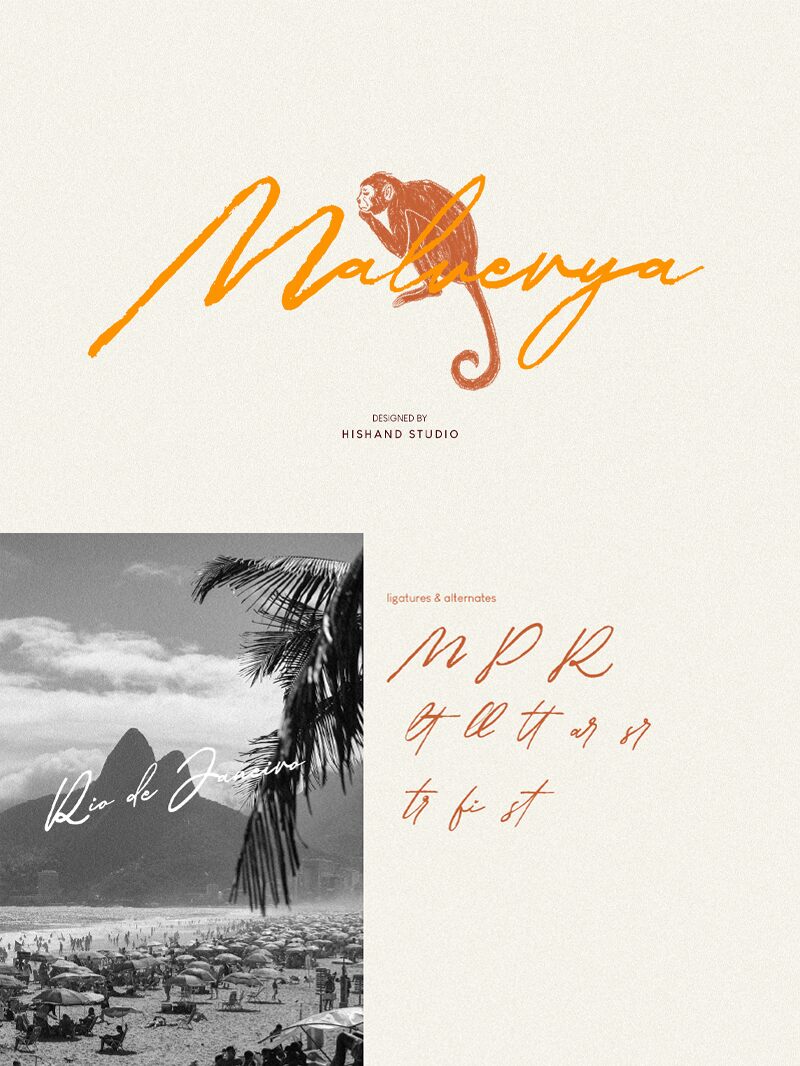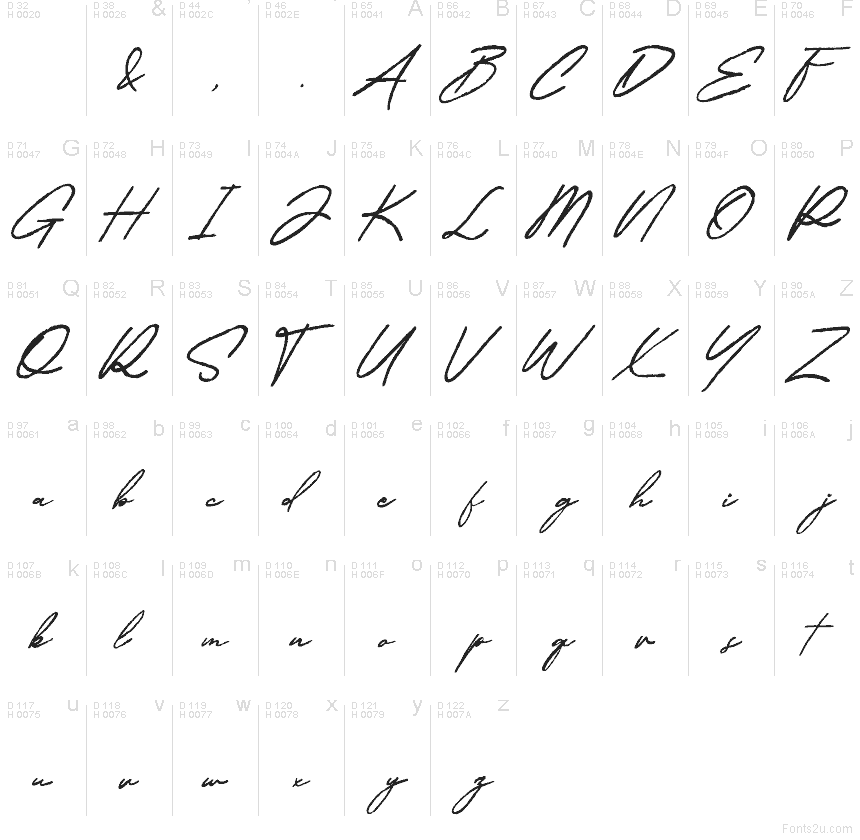
Malverya od Hishand Studio to darmowy font odręczny, kształtowany przez szybki, wznoszący się rytm i długie, zwężające się pociągnięcia, które sprawiają, że litery są w ciągłym ruchu. Dynamiczne początki i ostre zakończenia nadają mu charakter szybkiego pisma pędzlowego, zamiast zwykłego, niedbałego podpisu.
Ta energia doskonale sprawdza się w logotypach butikowych, opakowaniach, brandingu marek beauty, cytatach w mediach społecznościowych i nagłówkach zaproszeń, gdzie luźny, osobisty akcent wygląda naturalniej niż wygładzona kaligrafia. Krótkie tytuły i projekty oparte na nazwach zyskują najwięcej, ponieważ wydłużone znaki i pochylenie nadają każdej linii mocną, odręczną obecność.